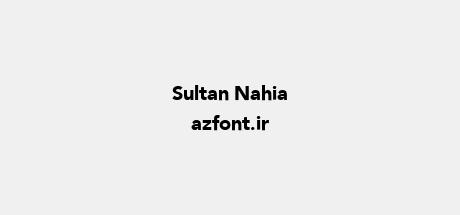
Sultan Nahia
فونت زیبای رایگان Sultan Nahia
قلم زیبای Sultan Nahia از سری قلم های بسیار زیبا برای تایپوگرافی و لوگو تایپ می باشد.این قلم در وزن Regular و توسط Dario Muhafara - Ghiath Alsory طراحی و منتشر شده است.
Linotype GmbH
Sultan Maktari
Sultan Nahia, designed by Sultan Maktari in 2005, is a modern Kufi and a winner in Linotype's first Arabic Typeface Design Competition. The design is very geometric and bold. This makes it suitable for large display sizes, especially in the area of advertising. The font includes a matching Latin design and support for Arabic, Persian, and Urdu. It also includes proportional and tabular numerals for the supported languages.